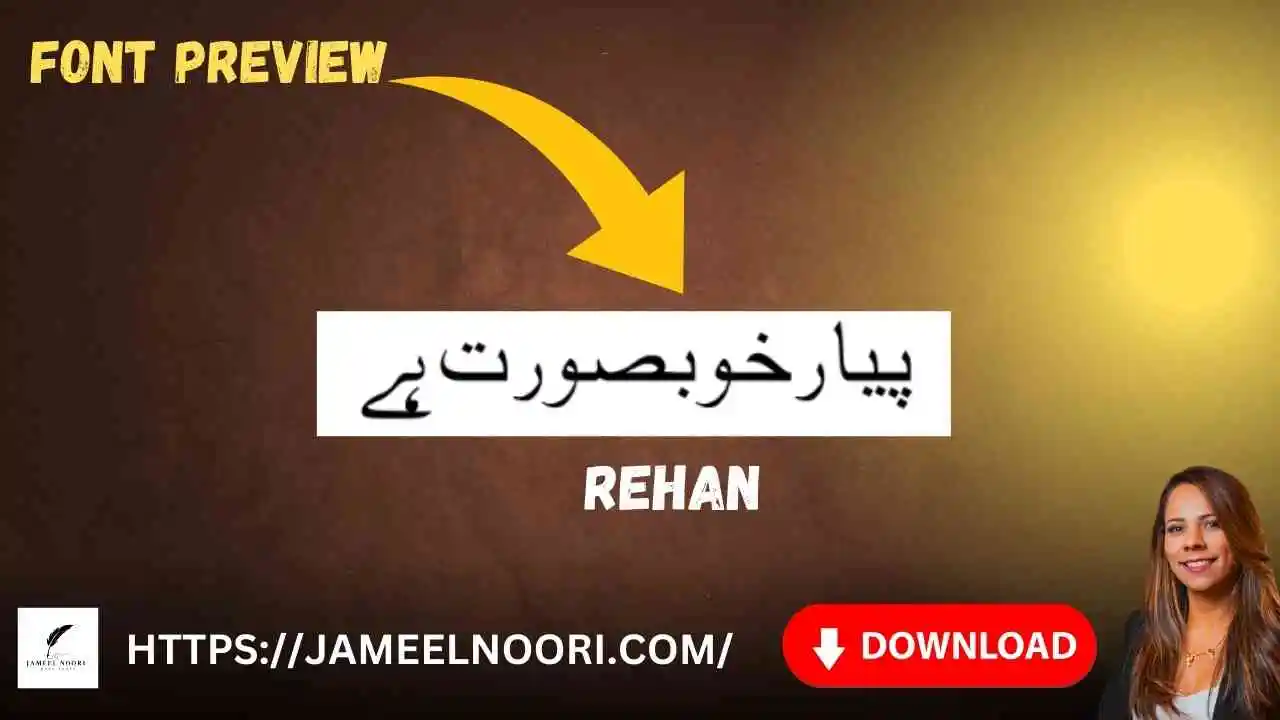
Download Urdu Font Rehan un users ke liye best choice hai jo apne documents, websites aur designing projects mein stylish aur readable Urdu text use karna chahte hain. Yeh font specially Pakistan ke writers, students aur designers ke liye design kiya gaya hai jo Urdu likhne ya digital designing ka shauq rakhte hain. Lahore, Karachi aur Pakistan ke dusre shehron mein yeh font bohot popular hai aur log isay free download karke apne projects mein use karte hain.
Quick Summary of Rehan Urdu Font
Features of Download Urdu Font Rehan
Download Urdu Font Rehan apne simple aur readable design ki wajah se mashhoor hai. Is font ke kuch khas features niche diye gaye hain:
- Easy readability for Urdu text
- Stylish aur elegant design suitable for books & web content
Why Choose Download Urdu Font Rehan for Your Projects
Download Urdu Font Rehan un logon ke liye perfect hai jo apni writing aur design projects ko attractive banana chahte hain. Iska modern style aur clear readability isay best Urdu fonts me shamil karta hai. Chahe aap books likh rahe ho, websites design kar rahe ho ya Urdu posts create kar rahe ho, Rehan font aapke content ko professional aur stylish look deta hai.